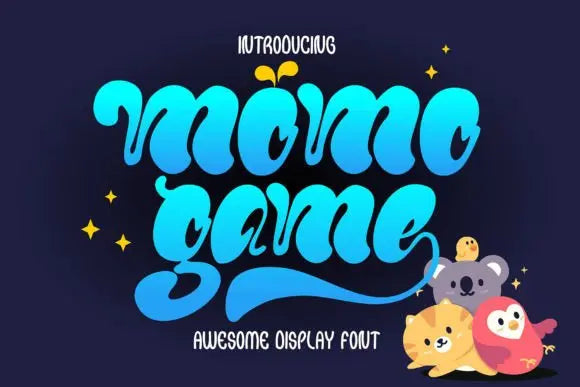
Fuente del juego Momo
“Momo Game” es una fuente de visualización entrañable que se caracteriza por sus personajes lindos y regordetes, con alternativas estilísticas.
Este divertido tipo de letra irradia un encanto caprichoso, lo que lo hace perfecto para proyectos que requieren un ambiente divertido y amigable. Con su tipografía dinámica y alternativas estilísticas incluidas, “Momo Game” ofrece versatilidad y carácter, lo que permite a los diseñadores crear diseños llamativos con facilidad.
Ya sea que se use para libros infantiles, marcas divertidas o carteles alegres, esta fuente agrega un toque de encanto y personalidad a cualquier proyecto, lo que la convierte en una excelente opción para los diseñadores que buscan un tipo de letra peculiar y dinámico.